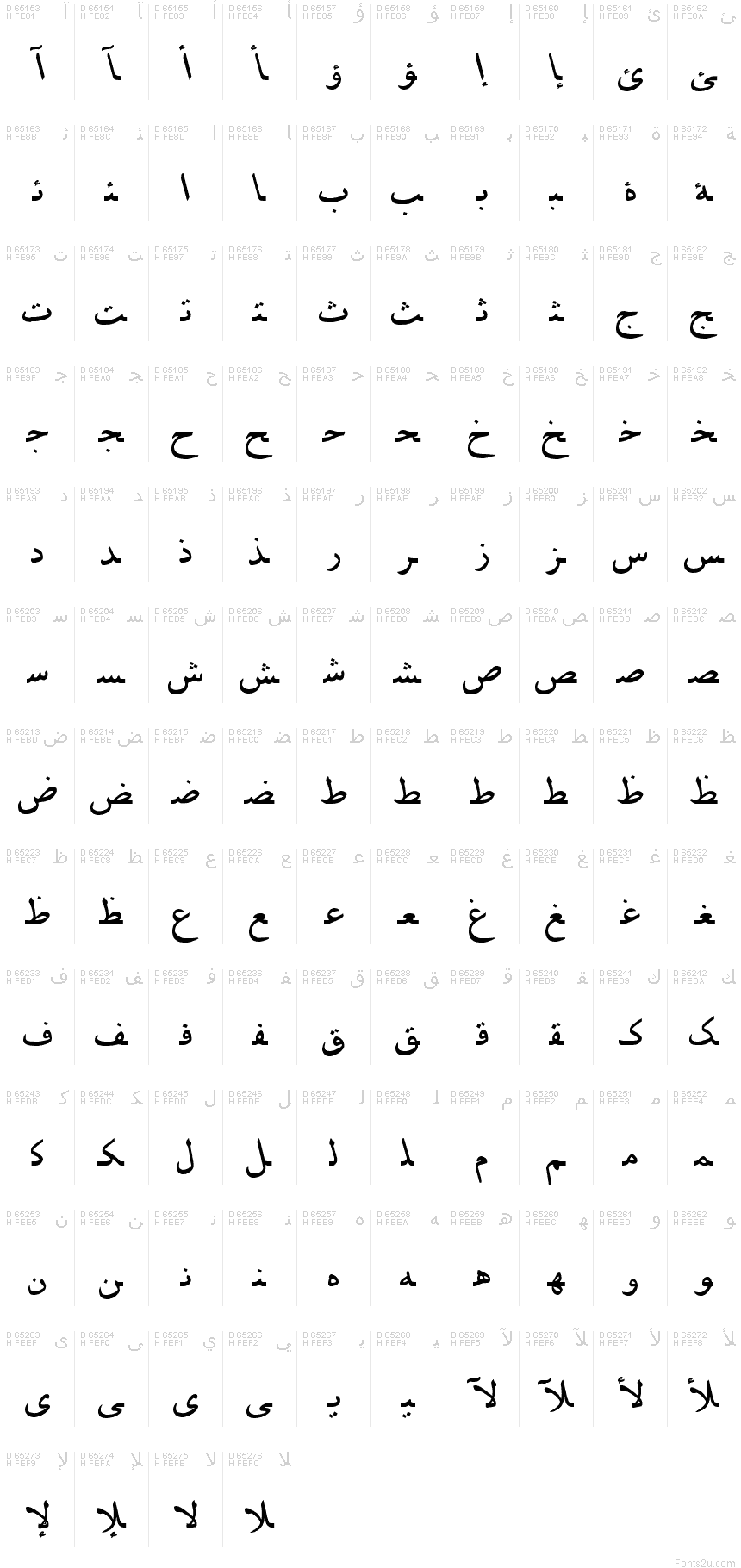
B Mashhad Bold Italic von Borna Rayaneh ist eine kostenlose arabische Display-Schrift mit einem schwungvollen, kalligrafischen Charakter. Die Buchstaben wirken zugleich dicht und fließend, mit kräftigen Strichen, spitzen Verbindungen und einem lebendigen Rhythmus, der der Schrift eine handschriftliche, headline-taugliche Präsenz verleiht.
Sie ist ideal überall dort, wo Arabisch eine starke dekorative Stimme braucht: Buchcover, kulturelle Poster, Veranstaltungstitel, Verpackungen und Magazin-Schlagzeilen. Als kostenlose Schrift eignet sie sich auch perfekt für kurze Branding-Phrasen, Titelkarten und Zitate – besonders dann, wenn Sie möchten, dass die geneigte Bewegung und das kompakte Gewicht der Schrift die Komposition ganz allein tragen.
Zeichentabelle der Schriftart B Mashhad BoldItalic
Zeichentabelle von B Mashhad BoldItalic: Arabische Präsentationsformen-B, Seite 1
Glyphen der Schriftart B Mashhad BoldItalic — Arabische Präsentationsformen-B, Seite 1